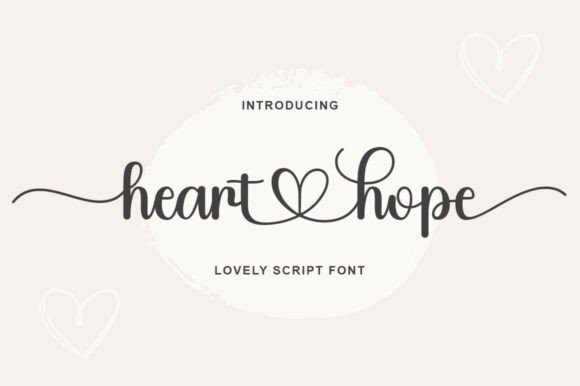
Heart Hope
Encontrar os elementos de design certos pode ser um desafio, mas Heart Hope oferece uma coleção excepcional que eleva o seu trabalho instantaneamente.
Trabalhado com precisão, Heart Hope fornece vetores limpos, tipografia suave e uma licença comercial para sua tranquilidade.